Digitale Neuinterpretation klassischer Schriftarten
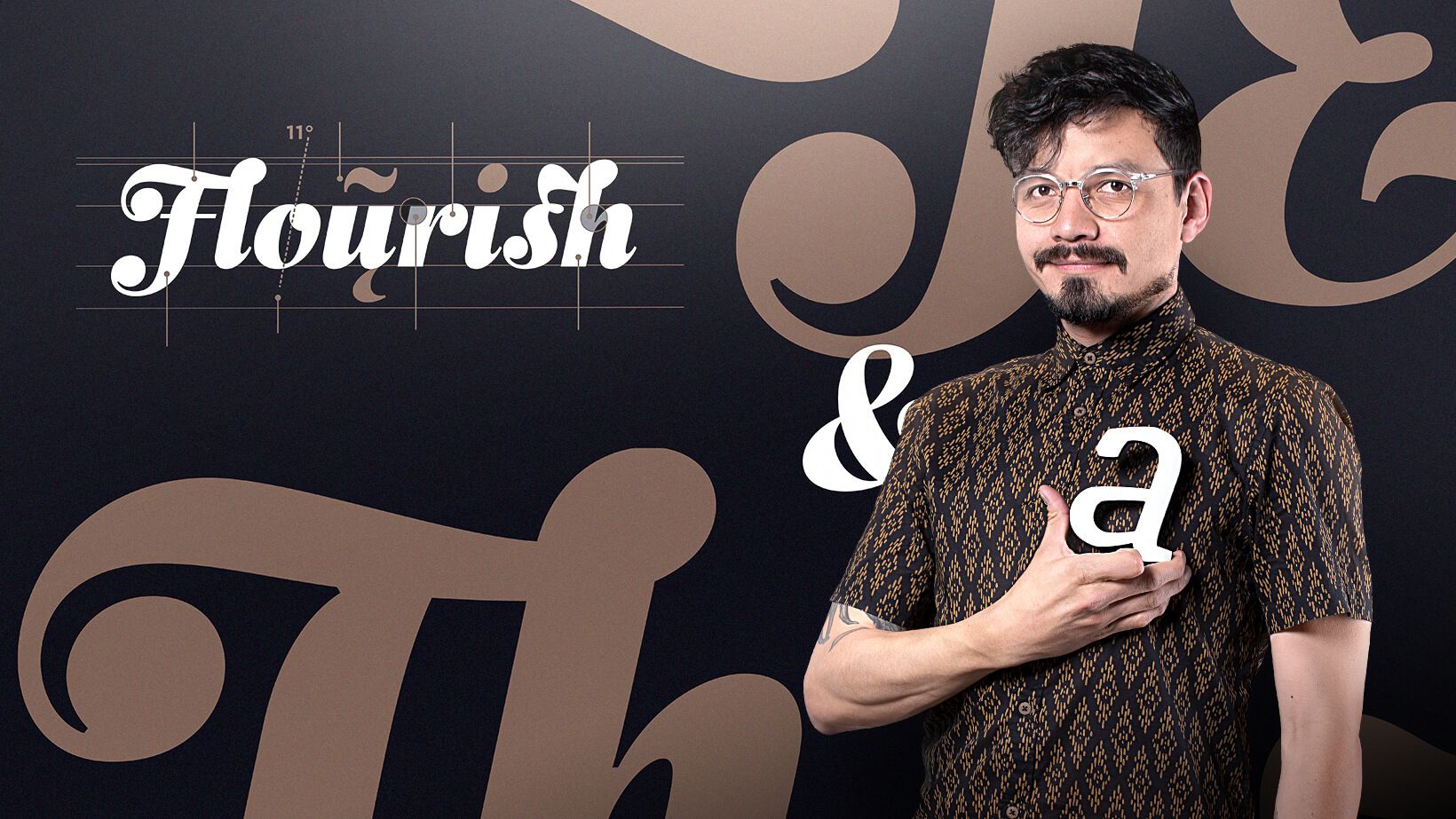
Lernen Sie die Methode der typografischen Wiederbelebung kennen, um alten Schriftarten ein neues digitales Leben zu verleihen
Tauchen Sie ein in die Welt der Typografie und unternehmen Sie eine Reise in die Vergangenheit. In diesem Kurs lernen Sie, die Wurzeln einer Schrift zu studieren, um sie digital neu zu interpretieren. Dies ist eine Art Hommage an die Vergangenheit aus der Hand von Oscar Guerrero - Grafiker und Spezialist für Typografie -, der Sie Schritt für Schritt mit der Methode von Wiederbelebung typografisch.
Wenn Sie einer klassischen Schrift ein neues digitales Leben geben möchten, lernen Sie mit Oscar und tauchen Sie in Zeichen, Formen und Flecken ein.
Sie werden eine alte Schrift Ihrer Wahl neu interpretieren, um ihr durch Design ein neues Leben in digitaler Form zu geben.
Einführung
Ein willkommener Gruß und eine Einführung
Einflüsse
Was ist eine typografische Wiederbelebung?
Typografische Archäologie
Auf der Suche nach der verlorenen Typografie
Archäologische Quelle
Methode: Klassifizierung
Methode: Ausgrabungen
Die Schrift verstehen
Metrik und Proportionen
Struktur, Farbe und Kontrast
Optische Offsets
Analoge Zeichnung und Anfangsbuchstaben
Morphologische Untersuchungen
Von analog zu digital
Zeichnen mit Illustrator
Zeichnen mit Glyphen I.
Zeichnen mit Glyphen II
Das System gestalten
Systematisierung Low Box
High-Box-Systematisierung I.
High-Box-Systematisierung II
Rhythmus und Abstand
Zeichensatz
Gedruckte Beweise
Abschlussprojekt
Neuinterpretation alter Schriftarten als Methode zum Erlernen des Entwurfs von Schriftarten